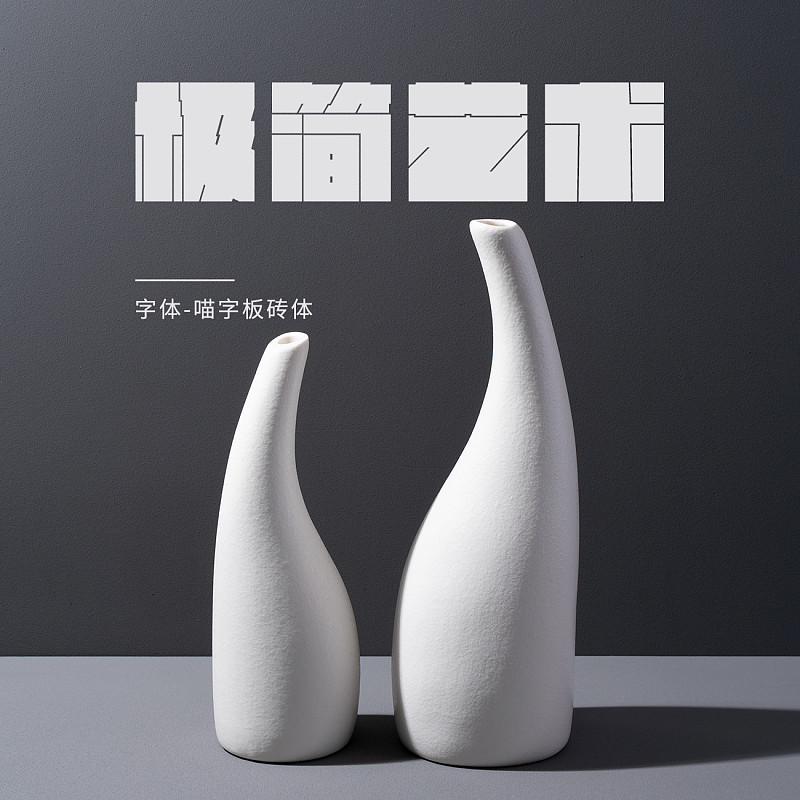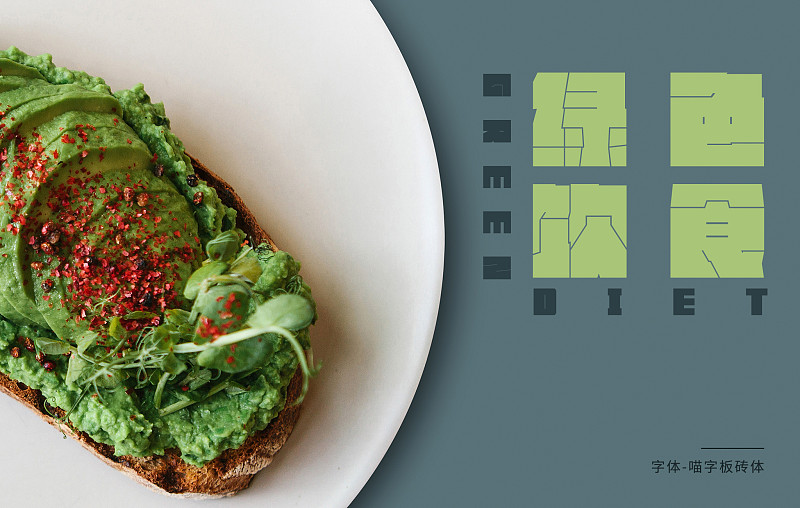
喵字板磚體
喵字板磚體是一款極具實驗性質(zhì)的細分字庫產(chǎn)品。該字在筆畫間隙的設計處理做到了極致壓縮,達到了以極小間隙突出整體力量感的設計目的。初步運用定位于裝飾性設計元素,具備豐富的字體運用空間。
字體類型:美術體
字體風格:美術字體, 廣告字體, 卡通動漫, 涂鴉, 超粗
字體用途:廣告, 動漫, 標題